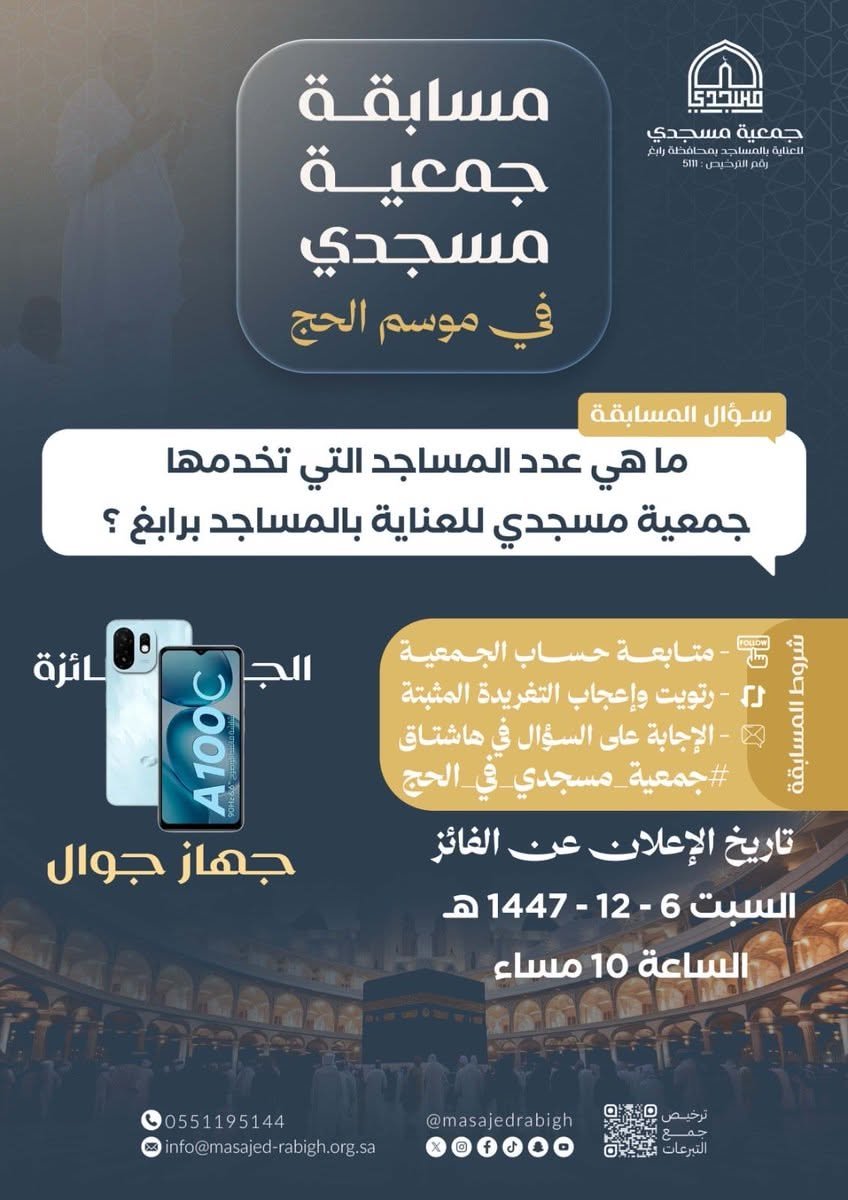
خط جمعية مسجدي — رابغ|iwan-zaza-typeface-arabic في أعمال جمعية مسجدي — رابغ
جمعية مسجدي — رابغ
إيوان هو خط عربي حديث عالي التباين من تصميم أحمد ظاظا، مستوحى من الطابع الكوفي ومتأثر بأسلوب النسخ. يوازن بين الذائقة الكلاسيكية والمعاصرة بفتحات داخلية واسعة وصواعد ونوازل قصيرة تقلّل الارتفاع، مع تباين عالٍ بين الرأسي والأفقي ينسجم مع اللاتيني. يضم خمسة أوزان من الخفيف إلى الأسود، ومجموعة واسعة من البدائل والحروف المركبة، ما يجعله مناسبًا للهويات البصرية والتحرير والتغليف والإعلان.
خط جمعية مسجدي — رابغ|iwan-zaza-typeface-arabic في تصميم من جمعية مسجدي — رابغ